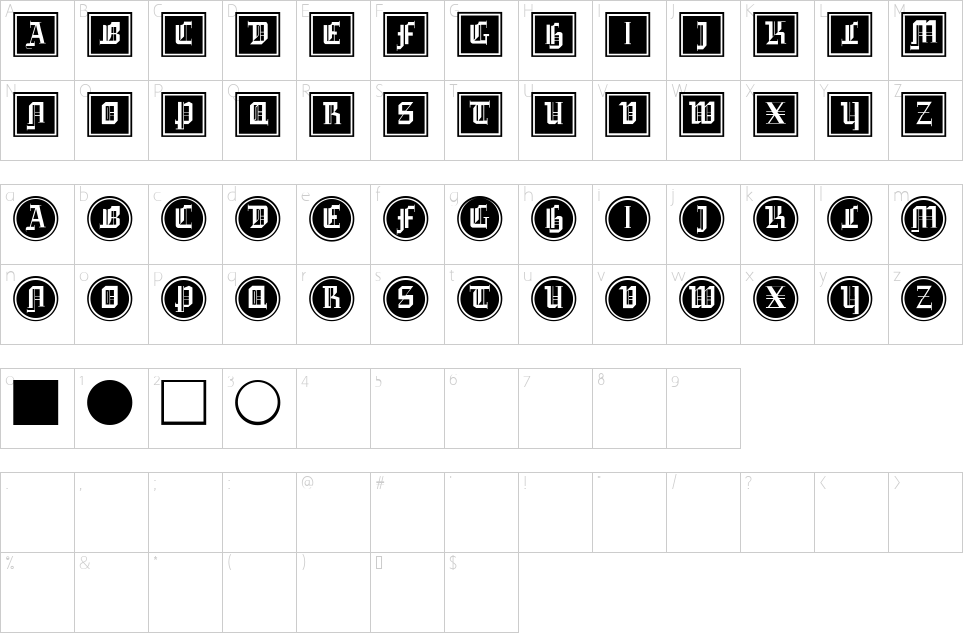
Descubra a origem inconfundível e moderna da Gotika Buttons Font! Essa elegante família de caracteres foi criada por Manfred Klein 函Klein, oferecendo um estilo único que combina clássico com futurista. Com seus contornos incisivos e linhas diretas, a Gotika Buttons é perfeita para criar designs impactantes em qualquer plataforma – seja Windows ou Mac. Esta fonte foi baixada por 2353 usuários devido ao seu design único e eficaz, oferecendo uma escolha gratuita para aqueles que buscam um estilo arrojado sem pagar nada. Descubra agora a versão completa da Gotika Buttons Font no site dos 1001 Free Fonts e adorne seus projetos com essa peça de gráficos única.